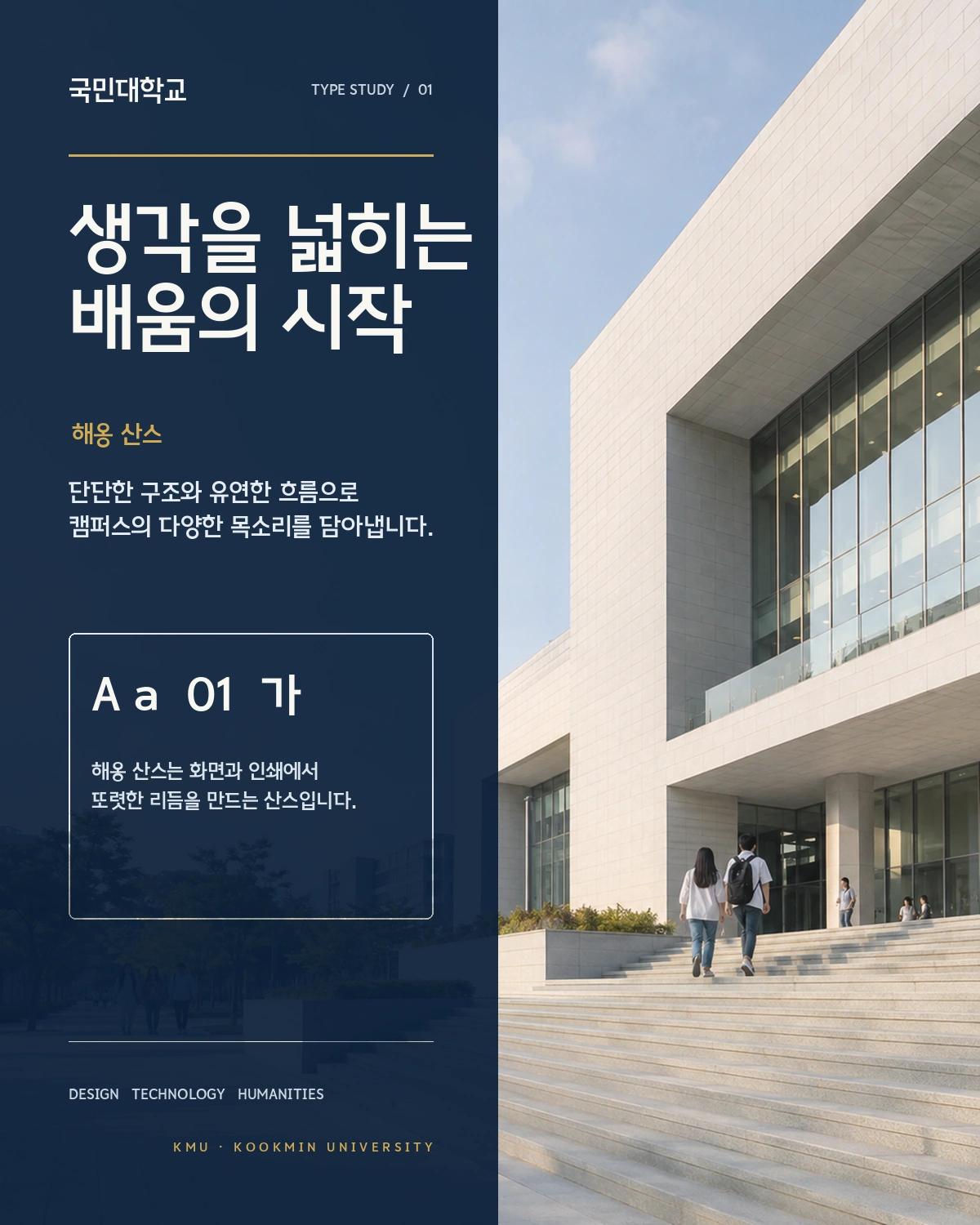
국민대학교 해옹 산스 — 국민대학교에서 배포하는 무료 폰트입니다. 성곡 세리프와 한 벌로 나온 부리 없는 골격의 서체로, 현대적인 감각을 담은 가변 산스
국민대학교 개교 80주년 전용 서체 가족에서 부리가 없는 쪽입니다. 성곡 세리프와 한 벌로 나왔습니다.
이름의 해옹에 대해서는 조심스럽게 적어야 합니다. 대학 측은 이 서체가 성곡 김성곤 선생의 장남인 김석원 회장의 도전과 혁신을 시각화했다고 설명하는데, 해옹이 그분의 호인지는 공개 자료에서 확인되지 않습니다. 대학이 붙인 문구는 글로벌 무대에서 멈추지 않는 도전과 혁신, 단합된 조직의 힘으로 미래를 선도한다는 것입니다.
네 스타일 가운데 가장 현대적인 인상을 맡습니다. 파일에서 재어 보면 받침 유무에 따른 높이 차가 거의 없는 네모틀이고 낱자는 정사각형에 가깝습니다. 폰트픽이 서비스하는 파일은 현대 한글 11,172자를 모두 담았습니다. 저작권 표시가 필수이고 수정과 2차 저작물 제작은 금지되니, 웹폰트로 서브셋을 다시 구워 쓰실 계획이라면 대학에 확인하시는 편이 안전합니다.